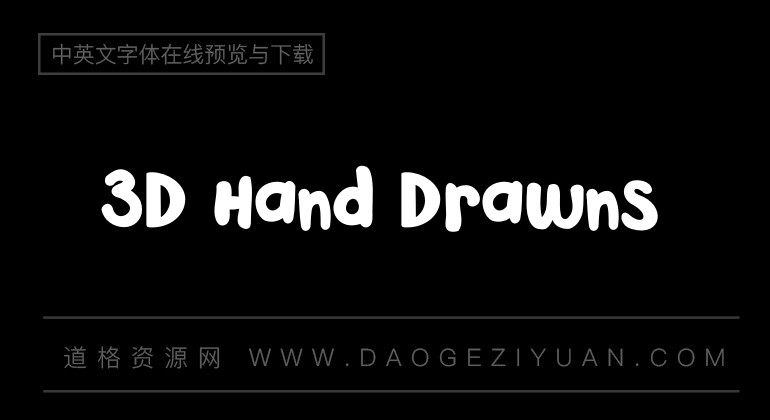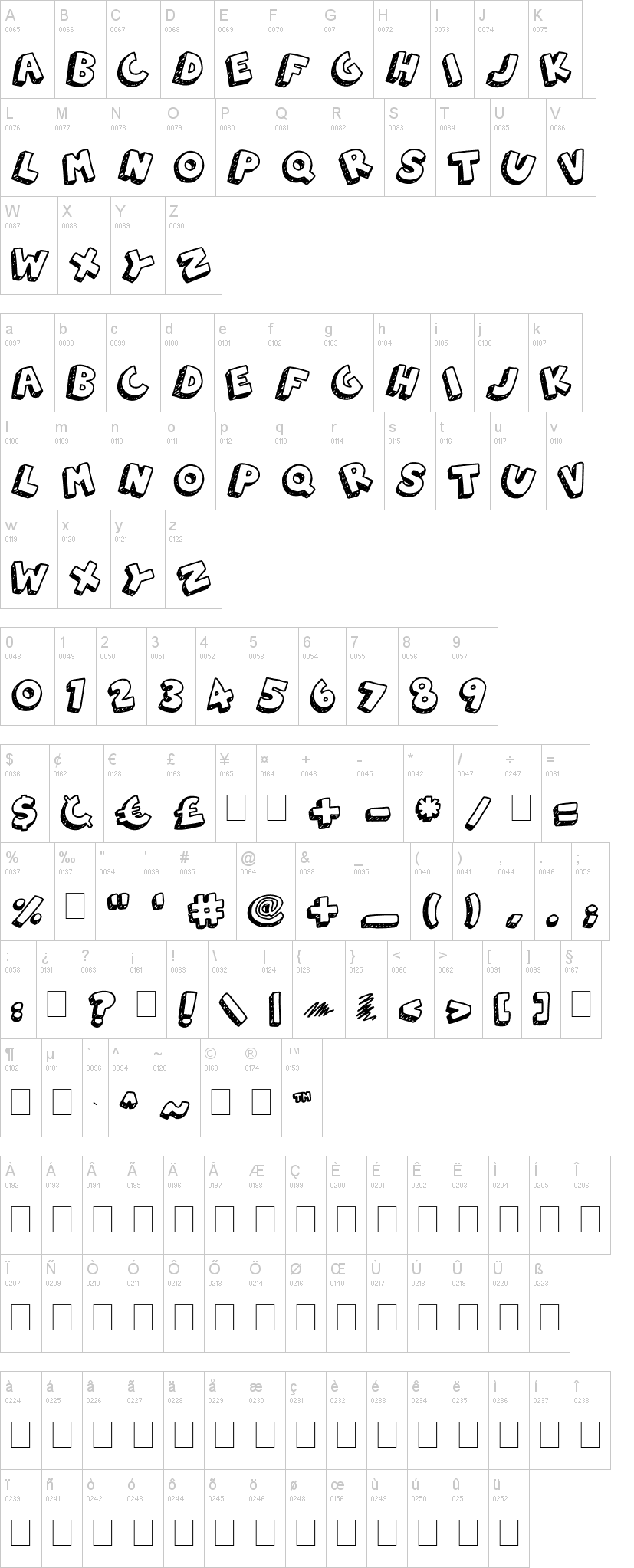
3D Hand Drawns
3D Hand Drawns 字体是一种手绘风格的三维立体字体,具有独特的立体感和抽象感。它的字形具有粗犷的轮廓线,可以在各种视觉元素中创造出不同的视觉效果。它可以用来制作海报、标志、标题等设计,也可以用来制作漫画、游戏等娱乐性设计。3D Hand Drawns 字体以其独特的视觉效果为设计师和视觉艺术家带来极大的创意空间。
3D Hand Drawns是一款非常不错的手写艺术字体,具有很好的视觉感,适合于文化类的宣传设计、商业类品牌的广告和产品包装设计以及个性化文字排版等较多场景。
3D Hand Drawns字符映射图